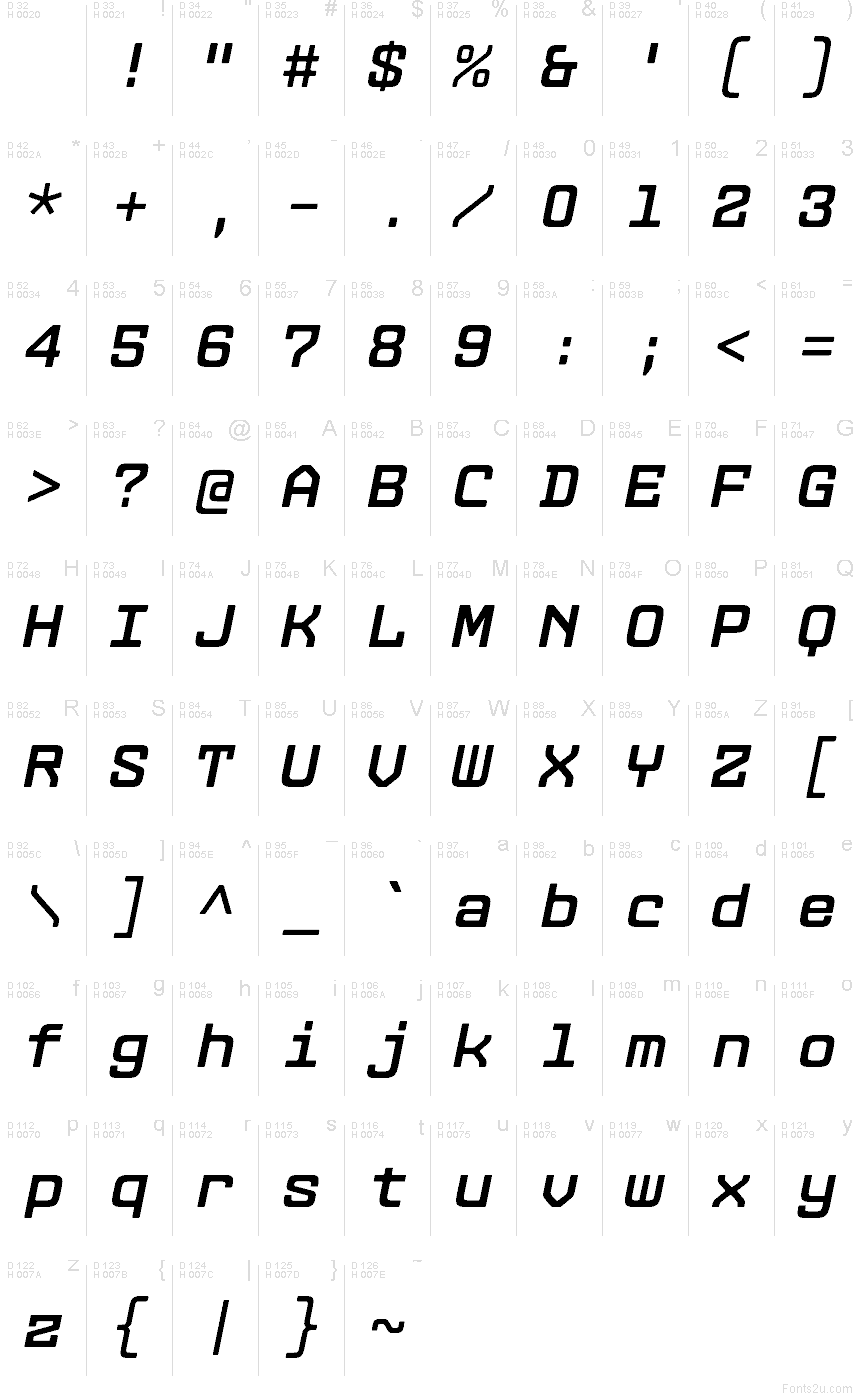
Dekatron SemiBold Italic, eine moderne Techno-Display-Schrift von Typodermic Fonts Inc., setzt voll auf Geschwindigkeit mit breiten, nach vorne geneigten Buchstaben und einem fließenden, aerodynamischen Rhythmus. Die schrägen Formen wirken kompakt und stromlinienförmig; eine Mischung aus weichen Kurven und knackigen Verbindungen verleiht der Schrift eine synthetische Retro-Digital-Attitüde, ohne dabei steif zu wirken.
Sie eignet sich hervorragend für Gaming-Grafiken, Musik-Artworks, Sport-Branding, Poster-Überschriften und Titelkarten, bei denen eine kurze Zeile mehr von Dynamik als von Ornamenten lebt. Als kostenloser Font ist sie ideal für Logo-Skizzen, Cover-Texte und interface-orientierte Wortmarken geeignet, da die gewinkelten Buchstaben eine schnelle, durchgehende Silhouette bilden.